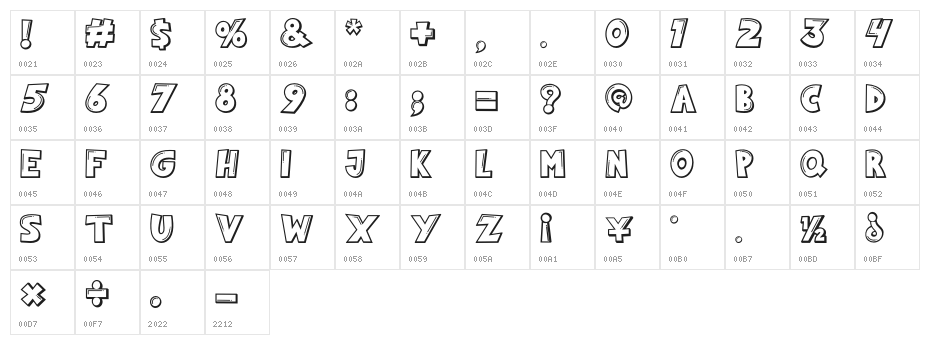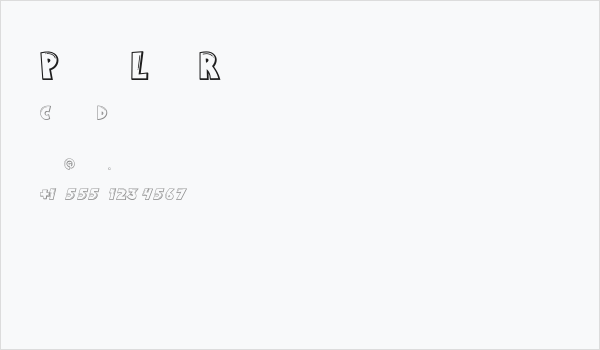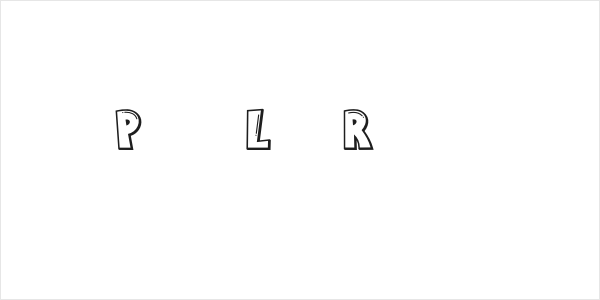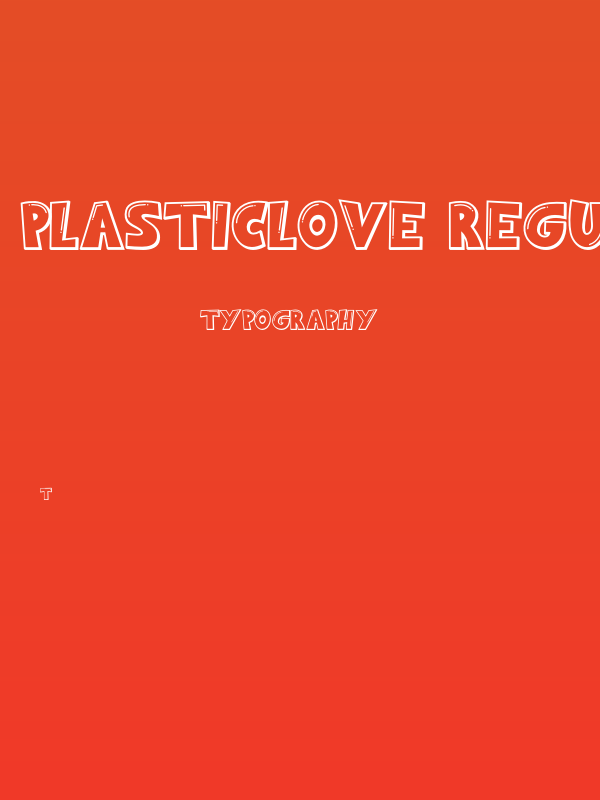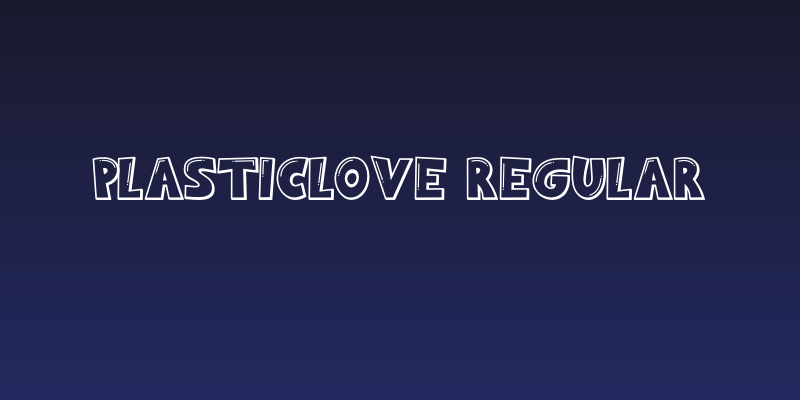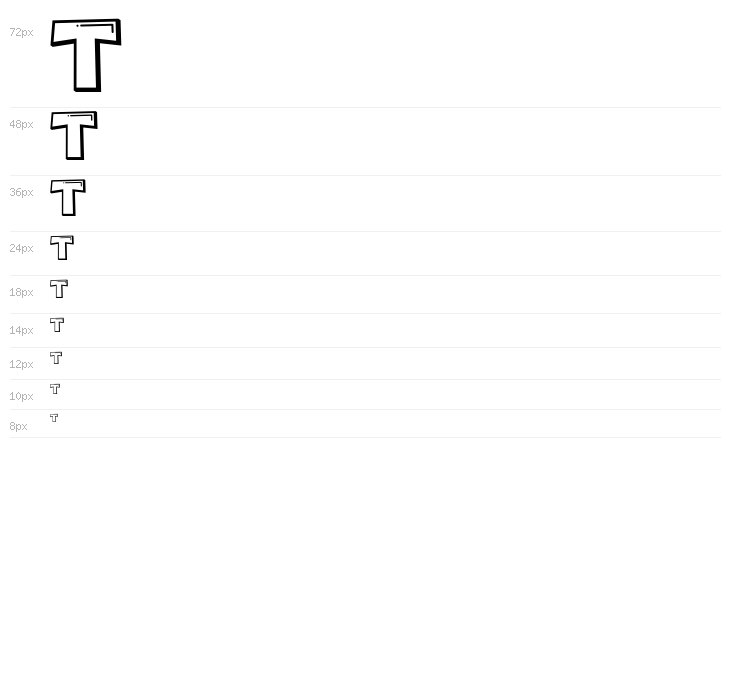
PlasticLove-Regular Font
| Stile generale | Playful, Comic |
| Caso d'uso | Headlines, Posters, Branding |
| Progetti proposti | Ideal for comic books, children's books, posters, and playful branding. |